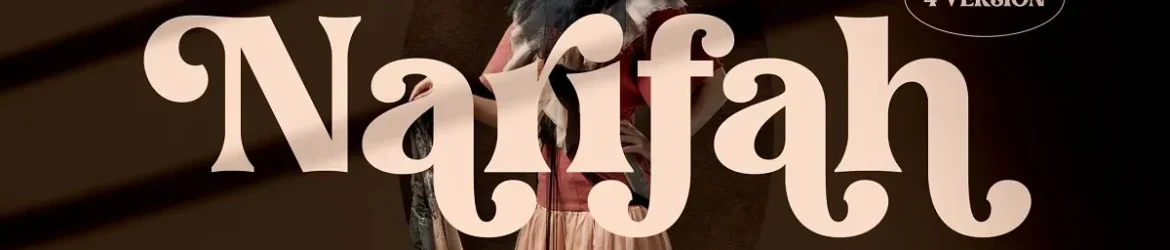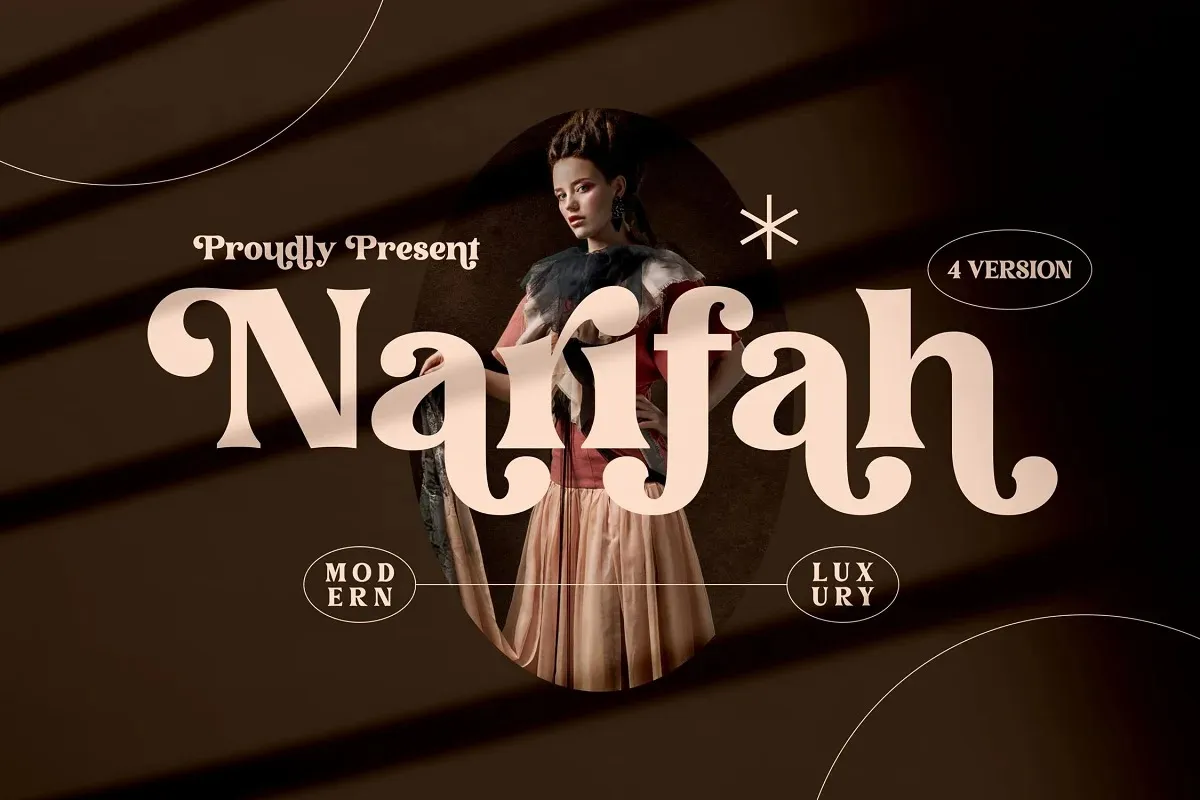
Narifah Font – Fonte Grátis
Narifah Font
A ‘Narifah Font’ é uma elegante serif que oferece um equilíbrio entre simplicidade e sofisticação. Inspirada no design de Storytype Studio, essa tipografia foi projetada para se destacar em estilos de marca requintados, como logos elegantes, títulos luxuosos de livros ou filmes, marcas de moda, revistas, etiquetas adesivas, além de letras e citações. A ‘Narifah Font’ é perfeita para qualquer ambiente que valorize a sofisticação e busca um tom delicado de estilo serif. Seja você designer gráfico, editora ou criador digital, esse recurso fonte é uma escolha brilhante para adicionar elegância às suas criações.